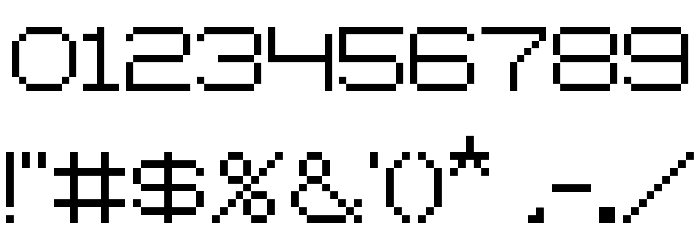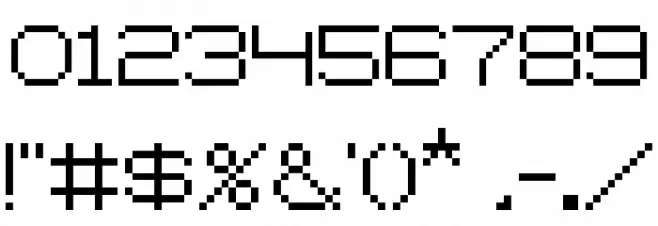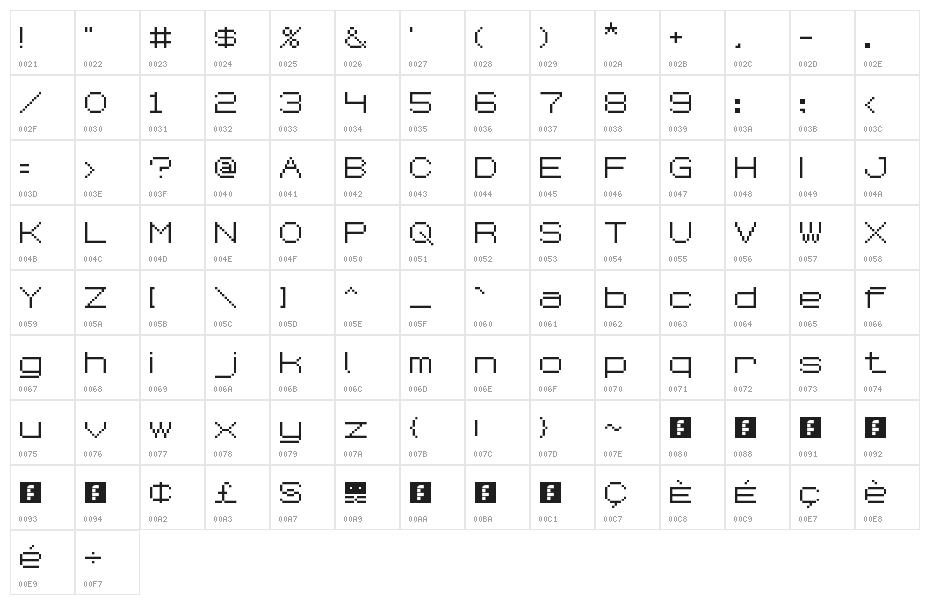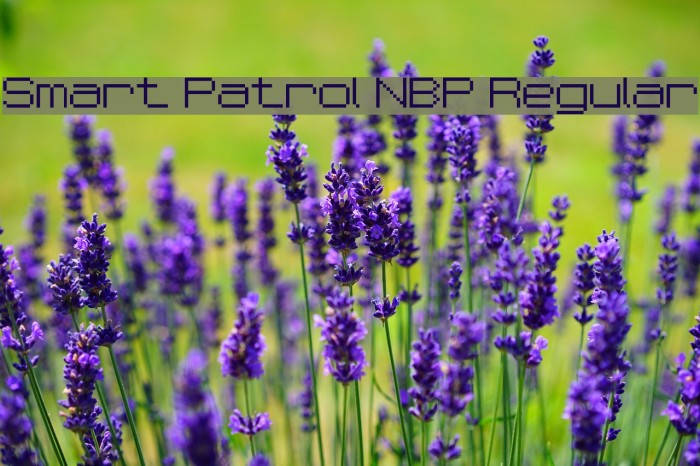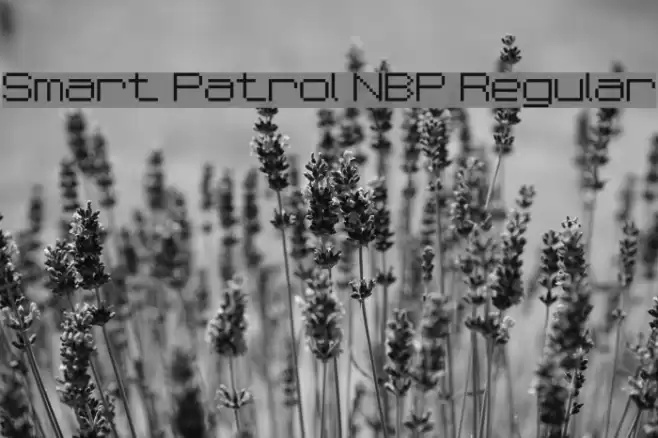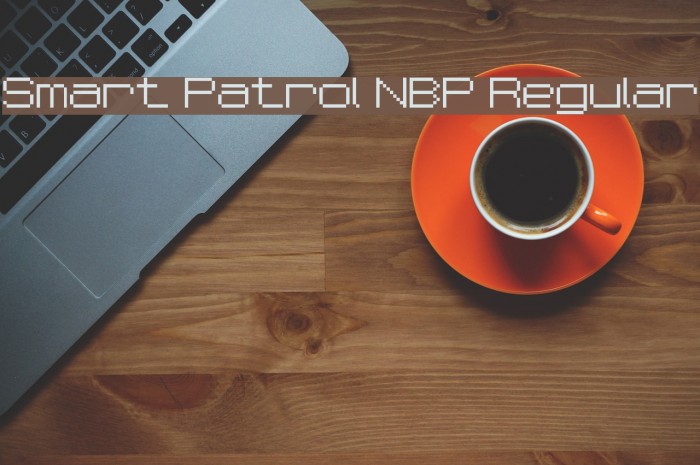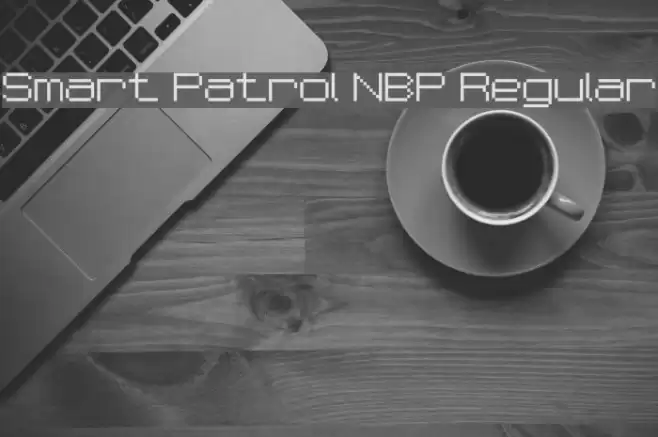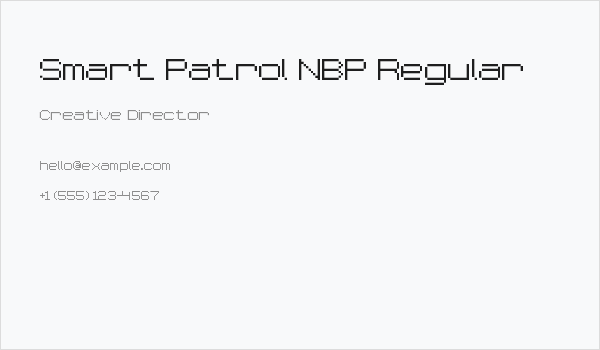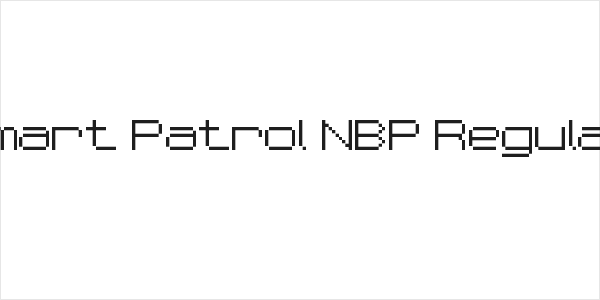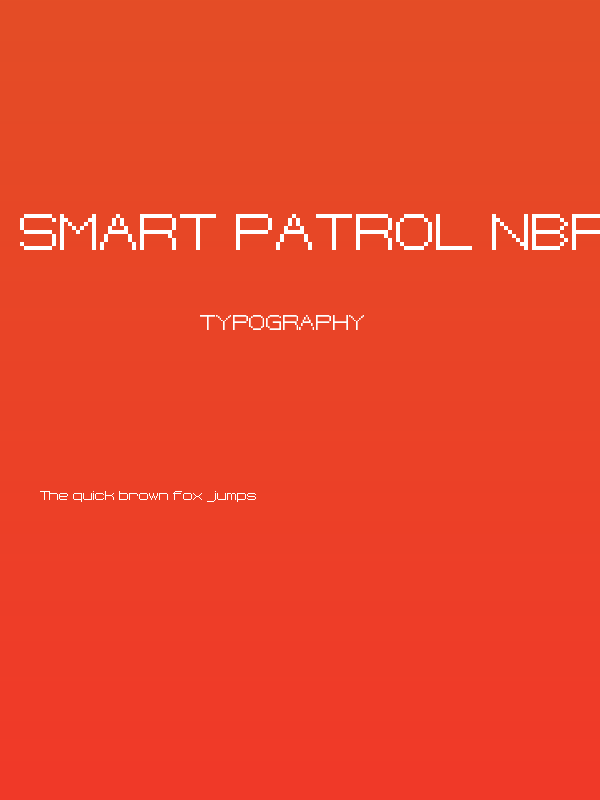
Smart Patrol NBP Regular Font
| समग्र शैली | Retro, Digital |
| उपयोग का मामला | Logos, Headlines, Posters |
| सुझाए गए प्रोजेक्ट | Ideal for video game design, digital art, retro-themed posters, and tech-related branding. |